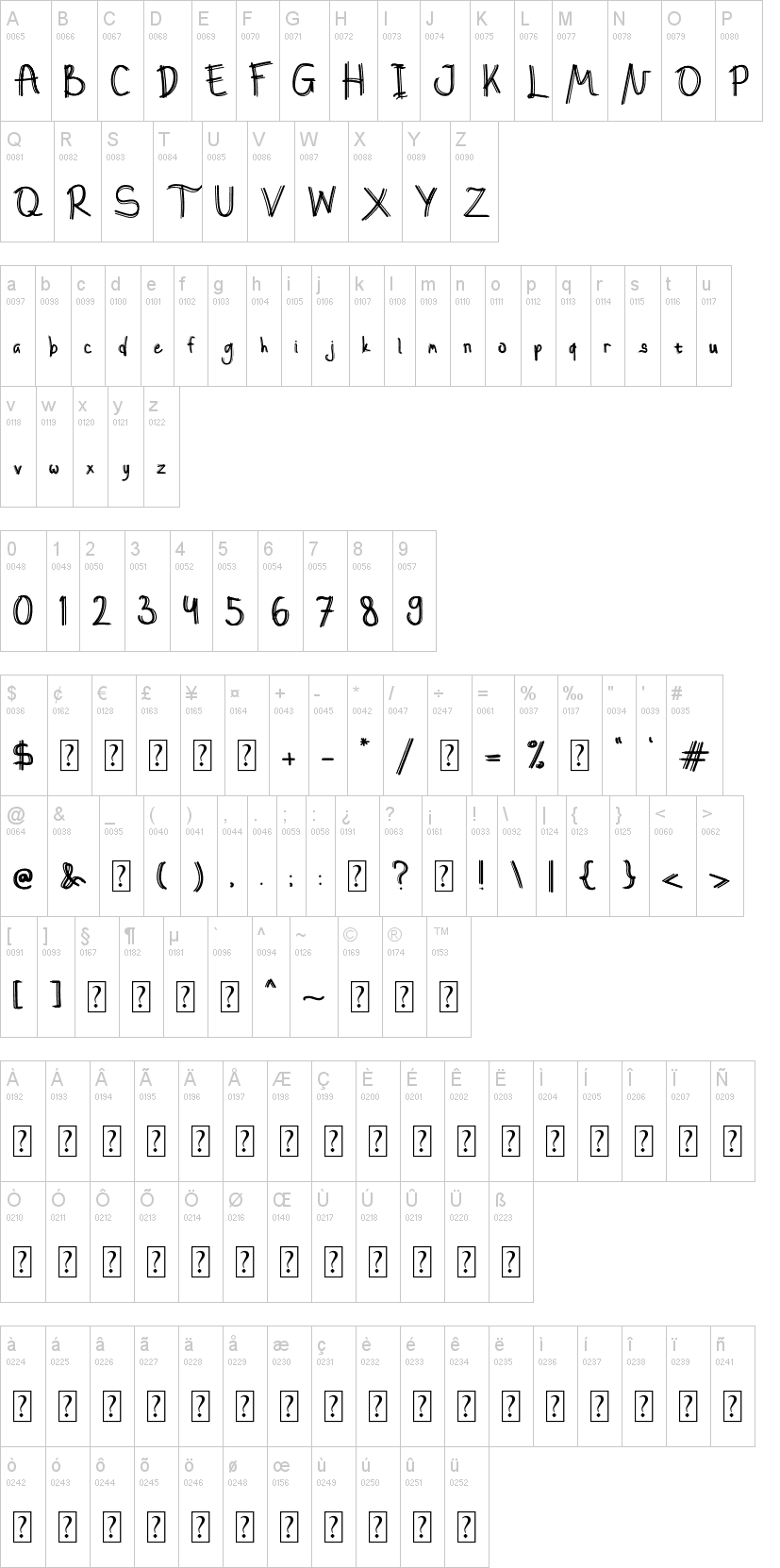
Loadtz 是一款免费的字体,由比利时设计师 Jan Fromm 创作。它拥有独特的设计,笔画粗细,自然的曲线,让您的文字看起来更加精致。它可以用于各种场景,如海报、书籍、网站等,可以满足您的各种需求。Loadtz 字体支持多种语言,可以在多种平台上使用,为您提供更多的设计选择。内容介绍
Loadtz是一款非常不错的手写艺术字体,具有很好的视觉感,适合于文化类的宣传设计、商业类品牌的广告和产品包装设计以及个性化文字排版等较多场景。